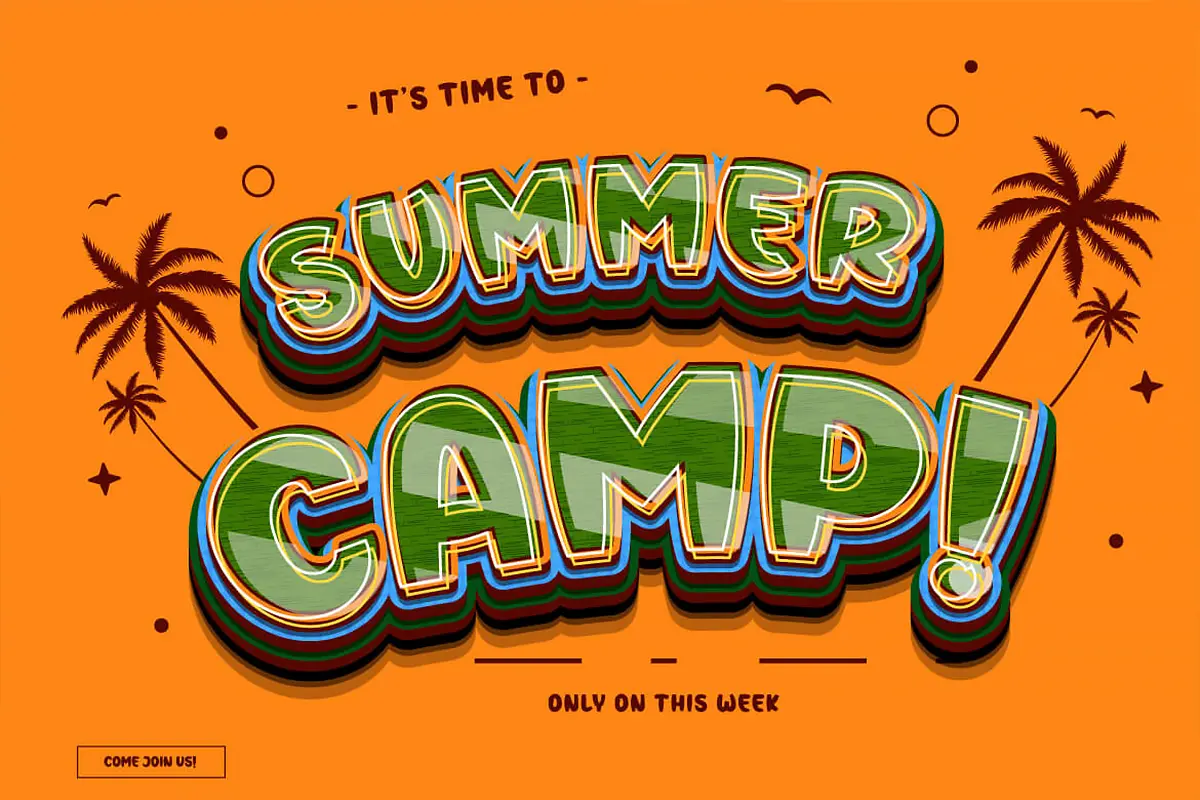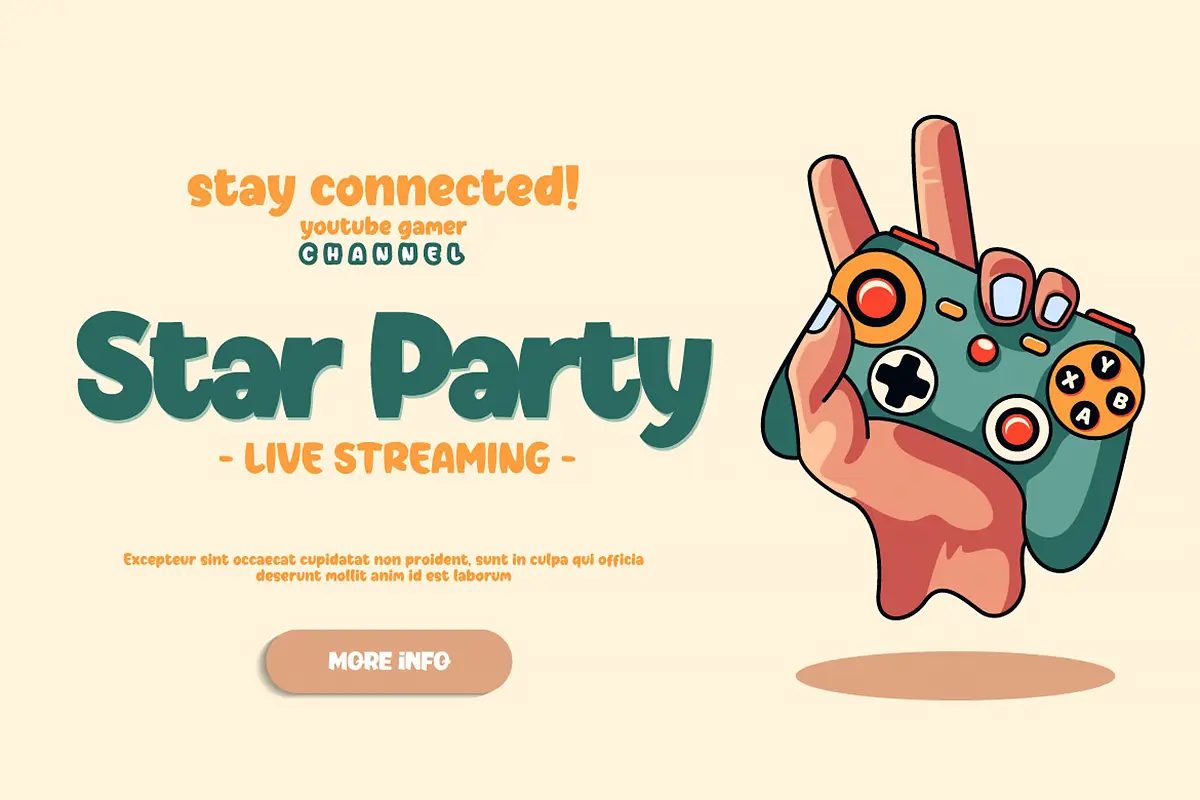
فونت سبک گیم Star Player
فونت Star Player یک فونت نمایشی سرگرمکننده، بازیگوش و جذاب به سبک گیم است که به طراحیهای شما حالوهوایی دوستانه و کودکانه میبخشد. این فونت برای پروژههایی که نیاز به لمس خلاقانه و فانتزی دارند، انتخابی عالی است و میتواند هر اثر شما را به سطحی متفاوت ارتقا دهد.
⭐ ویژگیهای محصول
- سبک نمایشی و بازیگوش
- مناسب برای طراحیهای کارتونی
- کاربردی در بازیهای کودکانه
- عالی برای پوسترها و پروژههای سرگرمکننده
- افزودن حس دوستداشتنی و خلاقانه به هر طراحی
🎯 موارد استفاده
- طراحی لوگوهای کودکانه و کارتونی
- ساخت پوسترهای سرگرمکننده و آموزشی
- استفاده در بازیها و اپلیکیشنهای کودکان
- افزودن حس شاد و فانتزی به پروژههای گرافیکی